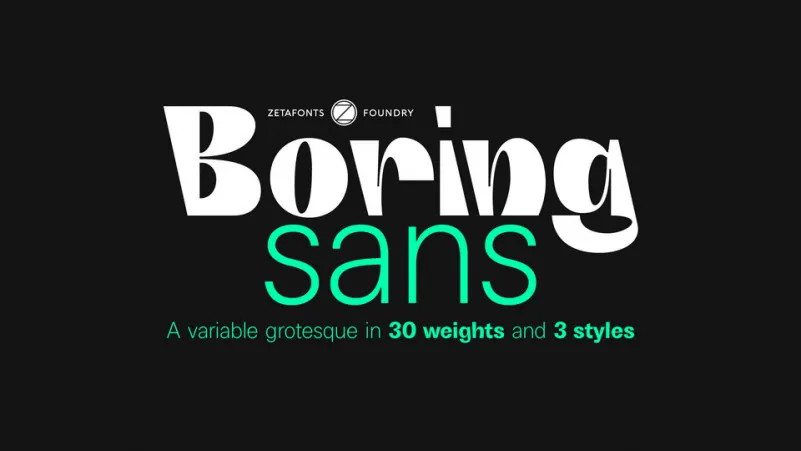
Esta é uma família moderna de tipo sans serif. Uma tipografia moderna e clara, mas com traços mais grossos que a maioria das outras. Boring Sans é ideal para criar títulos e headlines impactantes. Esta familia foi criada por Hamilton, não Cosimo Pancini como menciona o original em inglês. Mas mesmo sem esse detalhe, Boring Sans oferece um gosto único entre as famílias de tipo modernas sans serif. A família é uma tipografia variável que se concentra nos eixos de peso e estranheza. Esses dois parâmetros permitem aos designers explorarem a ampla gama de variações na design de tipo sans serif, começando com um conjunto neutro de proporções e evoluindo para um tratamento contrastado e dinâmico que certamente irá causar surpresa em uma rede social. Este novo lançamento da Zetafonts é perfeito para quem está buscando algo diferente e atraente para personalizar seu design, seja nas redes sociais ou em suas páginas web.